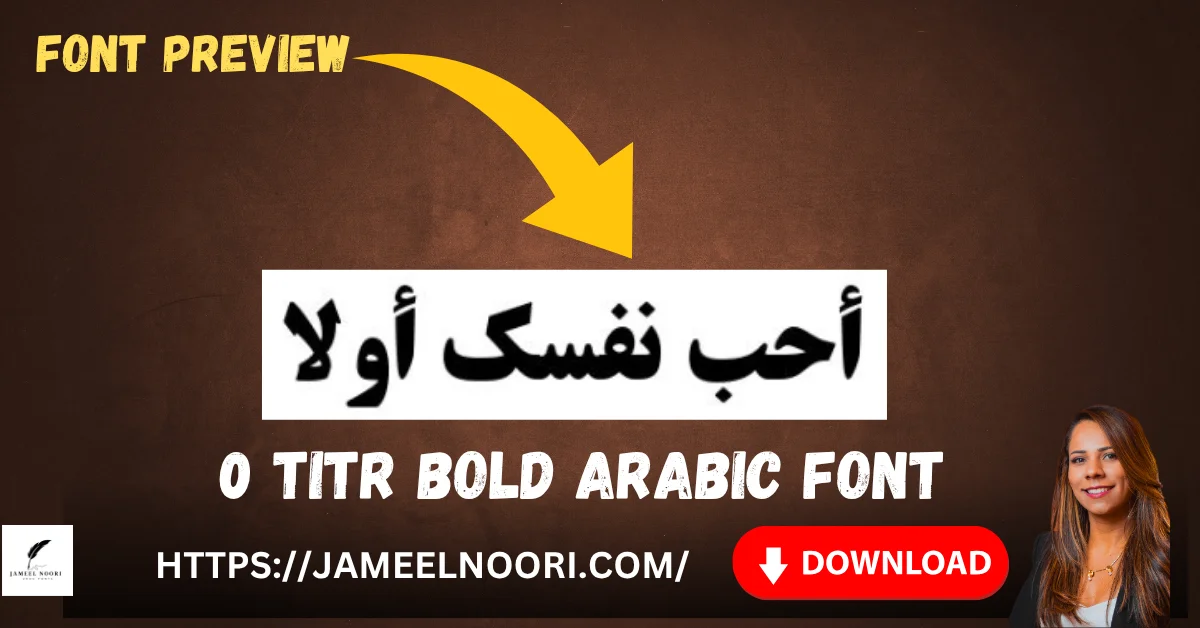
Abdo Master Bold Arabic Font – Complete Guide for Designers (Best & Latest Choice)
Abdo Master Bold Arabic Font bold Arabic typography preview for professional design
bdo Master Bold Arabic Font aik modern aur professional Arabic typeface hai jo duniya bhar ke designers aur content creators ke liye ek ultimate choice ban chuka hai. Ye font specially un logon ke liye design kiya gaya hai jo Arabic fonts, Urdu fonts, aur high-quality Arabic font download options search karte hain. Is font ka bold aur balanced style branding, logos, posters aur Islamic designs ke liye perfect hai.
Abdo Master Black Arabic Font – Powerful & Professional Arabic Typeface Font
Abdo Master Black Arabic Font bold calligraphy style preview
Abdo Master-Black Arabic Font ek powerful aur professional Arabic typeface hai jo modern designers, calligraphers aur content creators ke liye specially design kiya gaya hai.
Abdo Joody Bold Arabic Font – Powerful & Visually Strong Arabic Typeface
Abdo Joody Bold Arabic Font bold style Arabic typography preview
Abdo Joody Bold Arabic Font ek Bold TrueType Font hai jo apni strong strokes aur balanced letterforms ki wajah se kaafi popular ho chuka hai. Is font ko ab tak 10,171 se zyada dafa download kiya ja chuka hai aur 137 users ne isay 4.53 out of 5 rating di hai, jo iski quality aur usability ko clearly show karta hai.
Arghavan Bold Arabic Font example showing elegant bold calligraphy
Arghavan Bold Arabic Font ek modern aur stylish bold TrueType font hai jo designers aur calligraphy lovers ke liye perfect choice hai.
19 Khebrat Musamim Bold Arabic Font – Complete Guide for Worldwide Designers
19 Khebrat Musamim Bold Arabic Font aik Bold TrueType Font hai jo designers aur creative professionals ke liye perfect hai. Ye font ab tak 156,909 martaba download ho chuka hai aur 790 users ne isay 4.29/5 rating di hai. Is font ka unique style Arabic calligraphy me elegance aur readability dono provide karta hai. Is … Read more
0 Titr Bold Arabic Font – Most Widely Used Arabic Font
0 Titr Bold Arabic Font ki bold heading style aur modern Arabic typography preview
0 Titr Bold Arabic Font aik bohot hi mashhoor aur widely used Arabic font hai jo magazines, blogs aur digital headings me use hota hai. Yeh font apni bold TrueType styling ki wajah se bohot attractive lagta hai. Is font ka download count already 1,601,782 tak pohanch chuka hai aur 265 users ne isay 4.83/5 … Read more
Download Now - Janna LT Bold Arabic Font featured image showing elegant Arabic calligraphy design
Yeh font 615,430 martaba download ho chuka hai aur 1,614 users ne isay 4.43/5 rating di hai. Is font ki khasiyat iska elegant aur modern Arabic calligraphy design hai jo PowerPoint presentations, website designs aur creative projects ke liye perfect hai.